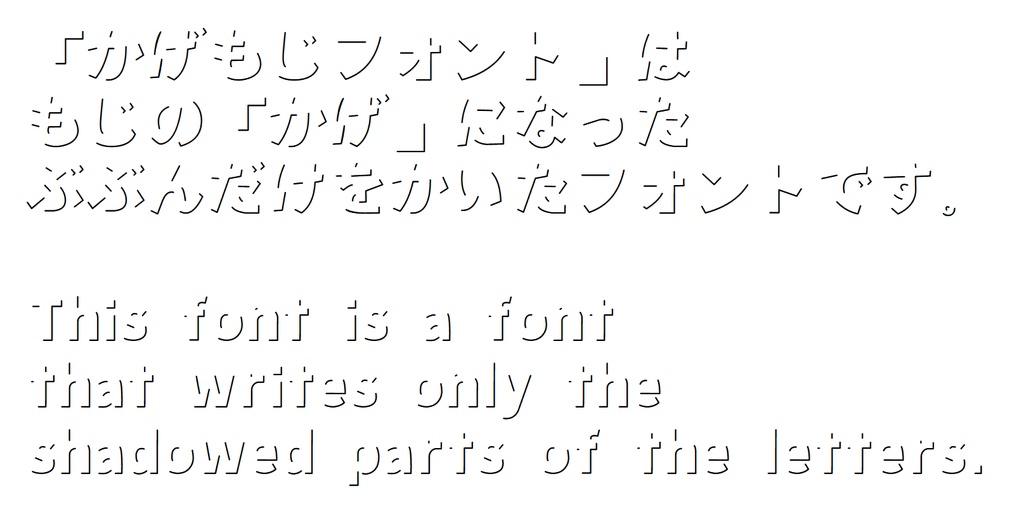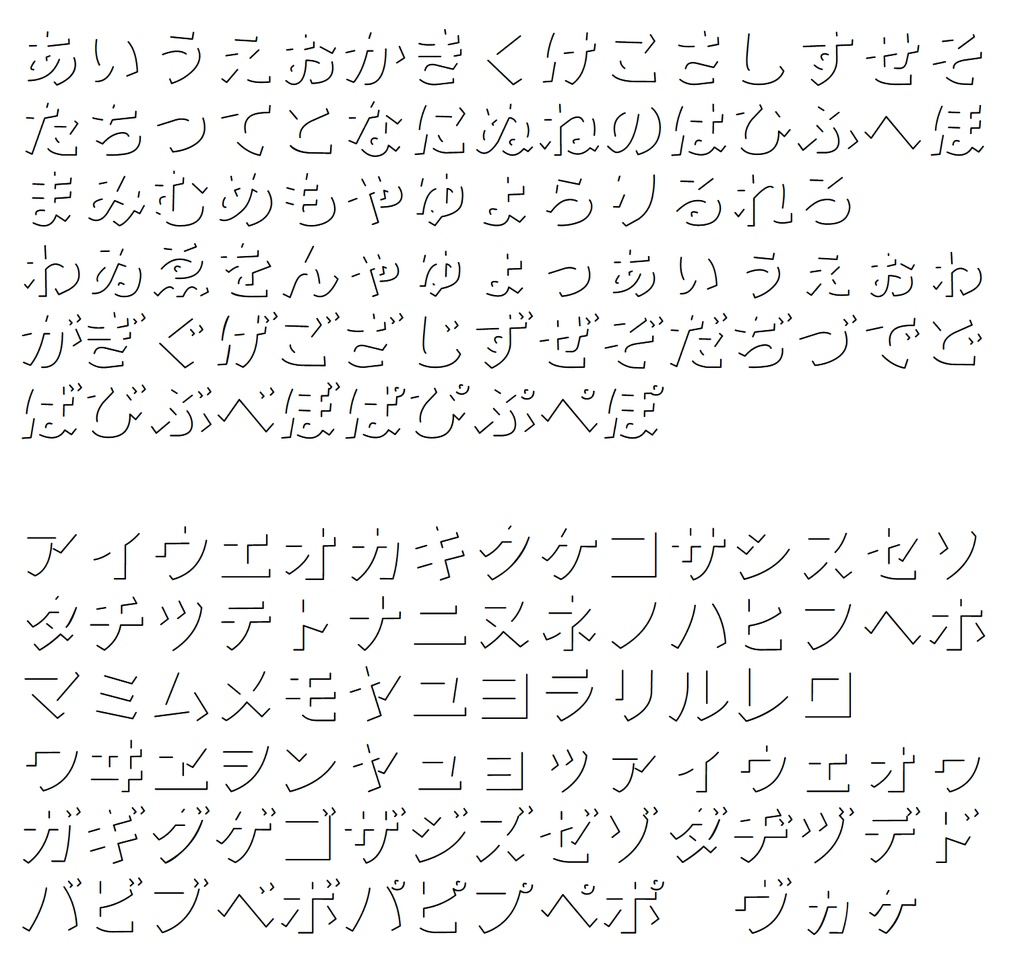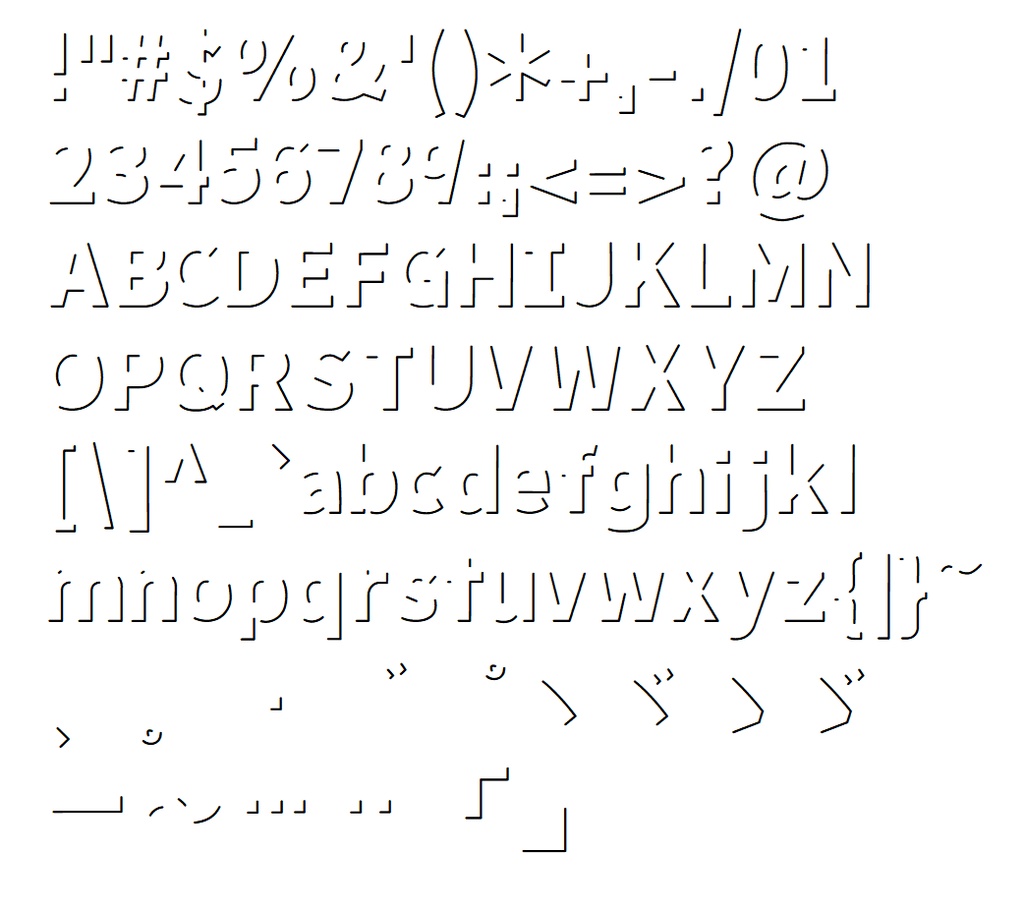
かげもじフォント (KagemojiFont)※漢字なし版
このフォントは文字の影になった部分だけを書いて作ったフォントです。 This font was created by writing only the shadowed parts of the letters. 尚、このフォントは自分好みの字体で書いています。 This font is written in my preferred style. 収録文字:ひらがな、カタカナ、半角英数記号と日本語用記号少し。 Characters included: Hiragana, Katakana, half-width alphanumeric symbols and some Japanese symbols. 商用利用可能(自己責任)、反社会的利用禁止でお願いします。 It may be used for commercial purposes (at your own risk), but anti-social use is prohibited. 追記:全角記号に「¥」も収録しています。 Additional note: The full-width symbol "¥" is also included.